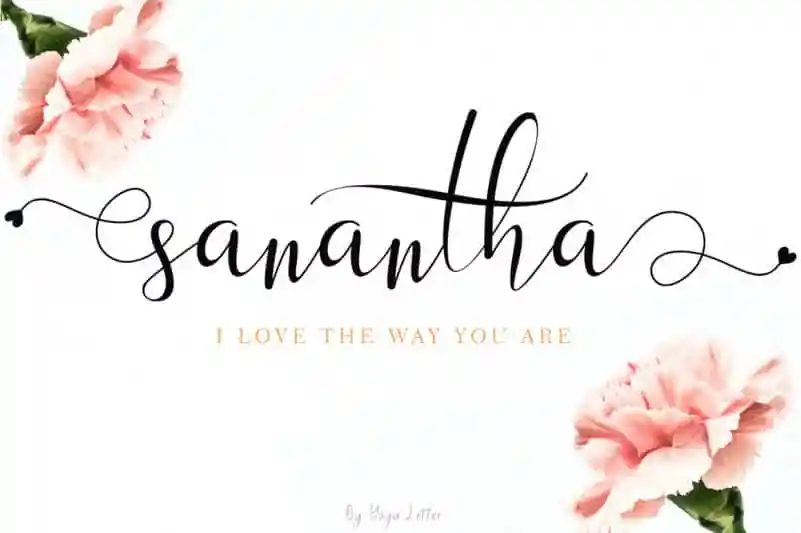
Sanantha Calligraphy Font – Download Grátis
Esta fonte chamada Sanantha Calligraphy Font é perfeita para aqueles que valorizam a beleza e a elegância no design. Feita com amor, esta fonte transforma qualquer trabalho em algo mais bonito e sofisticado. Ela se destaca não apenas como uma ótima opção para marketing de produtos ou para criar mensagens personalizadas, mas também é perfeita para trabalhos que exigem um toque delicado, como cartas de casamento, convites, logotipos, marcações e até mesmo status em redes sociais. É a escolha perfeita para capturar momentos especiais com uma graça única. Seja você criando sua própria identidade visual ou personalizando suas mensagens, Sanantha Calligraphy Font certamente fará toda a diferença.